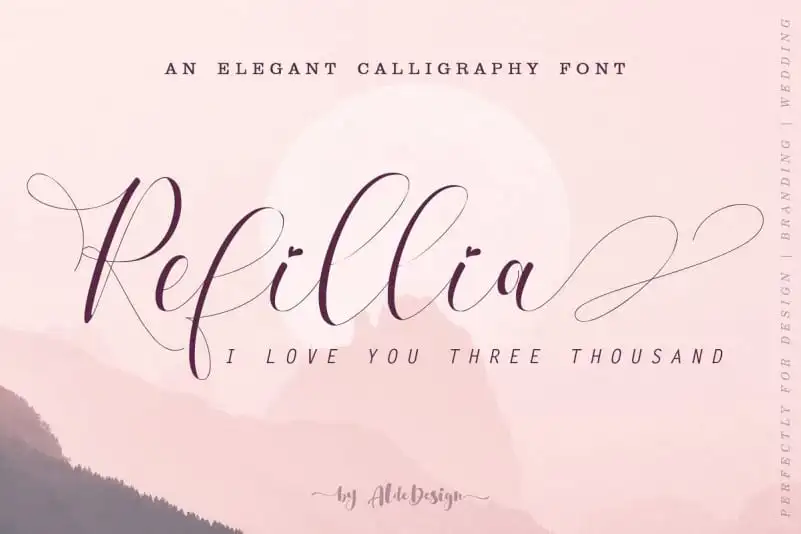
Refillia Calligraphy Font – Fonte Grátis
Refillia Calligraphy Font
Refillia Calligraphy é uma elegante tipografia de calligrafia cuidadosamente desenvolvida para adicionar um toque sofisticado a seus projetos. Esta fonte script apresenta uma tipografia limpa e profunda, com uma linha suave que combina elementos modernos e amorosos. Refillia Calligraphy é perfeita para aqueles que desejam incorporar delicadeza e modernidade em suas criações ou marcas de marca. Suas linhas variáveis no baseline e sua aparência atraente complementam perfeitamente os designs, tornando-a uma excelente opção para aplicar desde cabeçalhos até assinaturas, logotipos, selos, estampas, cartões postais e materiais de propaganda. Este é um fonte ideal para qualquer projeto onde deseja dar destaque com estilo e delicadeza.